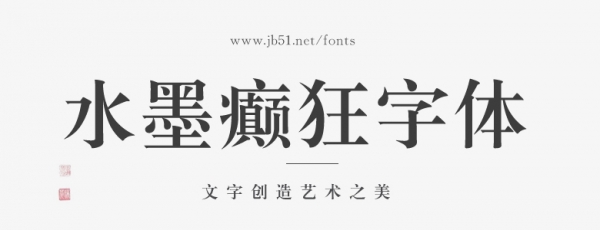
青鳥(niǎo)華光簡(jiǎn)小標(biāo)宋
青鳥(niǎo)華光簡(jiǎn)小標(biāo)宋是以草書(shū)的風(fēng)格為設(shè)計(jì)理念,其字形柔滑、圓潤(rùn),具有獨(dú)特的書(shū)寫(xiě)特色。該字體的筆畫(huà)精細(xì),排版時(shí)非常清晰,使得讀者在閱讀過(guò)程中無(wú)論是細(xì)節(jié)還是整體感受都具備優(yōu)秀的可讀性。